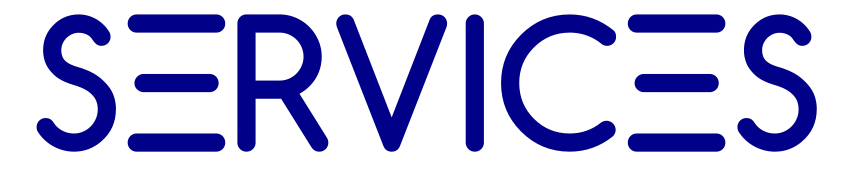
Vor Jahren erstellt, aber die Schriftart auf neuem PC nicht mehr vorhanden :(
Hallo, vor Jahren habe ich einige Bilder erstellt, aber auf meinem neuen PC ist die Schriftart nicht mehr vorhanden und ich habe offensichtlich auch keine Sicherung mehr 😞 Vielleicht kann mir jemand helfen, diese zu identifizieren?
Vom S her würde es passen, aber das E nicht ....